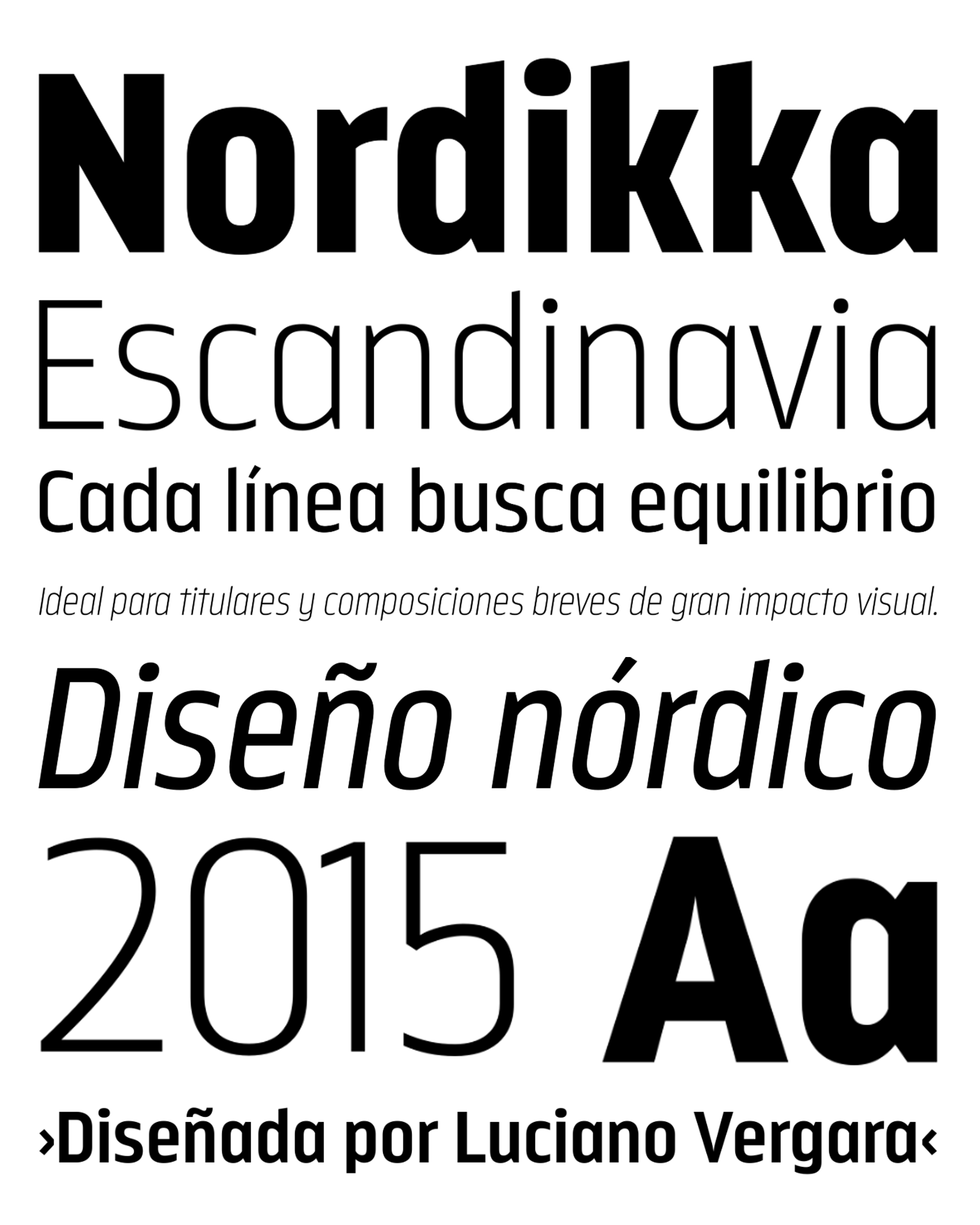
| Año | 2015 |
| Créditos | Luciano Vergara |
| Descripción | Nordikka es una tipografía sans-serif simple y pura de 10 estilos, diseñada por Luciano Vergara. Nordikka es una fuente condensada con una altura de x grande y terminales rectas, ideal para titulares y textos cortos. Una excelente opción para diseños limpios y visualmente atractivos. Nordikka se inspira en la cultura escandinava y su diseño, reconocido mundialmente, se caracteriza por sus formas puras, limpias y claras. La etapa final del proceso de diseño se completó en Olinda, Brasil, lo que inspiró algunas de las palabras de las muestras tipográficas, lo que permite reflejar una imagen de los hábitos y costumbres cotidianas de la gente. |
| Familia(s) | Nordikka |
| Estilos | 10 |